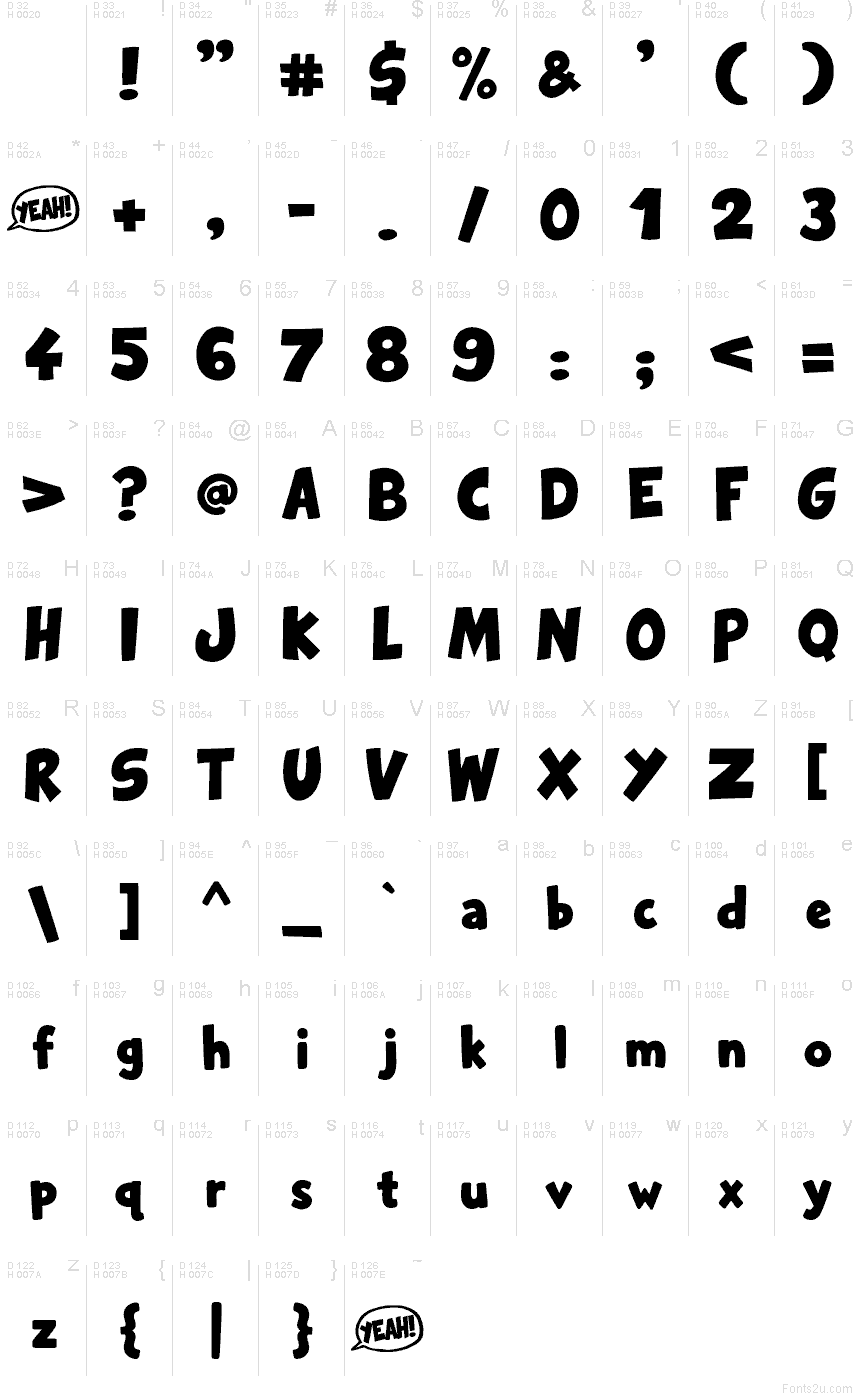
All Babies Channel, di Elise Benoit, è un font display gratuito in stile cartoon con un tocco giocoso tipico dei programmi per bambini. Le lettere sono corpose e dai bordi morbidi, con larghezze irregolari, una leggera instabilità e un aspetto artigianale che mantiene le forme grandi vivaci piuttosto che troppo levigate.
È perfetta per copertine di libri per bambini, confezioni di giocattoli, poster scolastici, inviti a feste e loghi allegri dove le forme devono risultare amichevoli e volutamente un po' goffe. Essendo un font gratuito, funziona benissimo anche per titoli brevi, cartelli e monogrammi semplici, poiché le lettere larghe e paffute mantengono il loro carattere anche in poche parole.